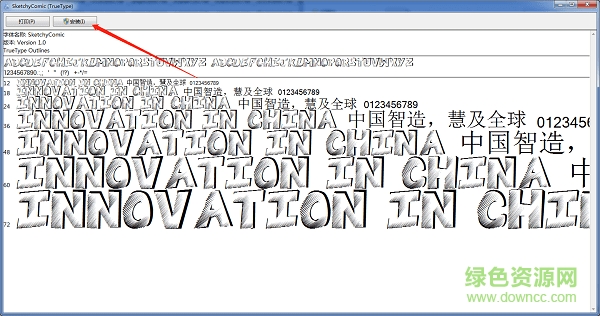
鉛筆素描字體是一款英文字體,字體整體以素描的形式為用戶呈現(xiàn),主要適用于英文,素描的展現(xiàn)形式能夠給用戶一種別樣的藝術(shù)體驗(yàn),非常適合日常設(shè)計(jì)中的使用,需要的用戶可來綠色資源網(wǎng)下載體驗(yàn)哦!
SketchyComic是一款非常漂亮的英文素描字體,擁有素描版的字體外觀,給你的感覺就像是畫出來的一樣,僅支持英文字母格式,讓你在電腦上也可以體驗(yàn)素描字體的美麗,比較適合作為漫畫、廣告設(shè)計(jì)、平面設(shè)計(jì)素材使用,一定能提升作品的顯示效果!